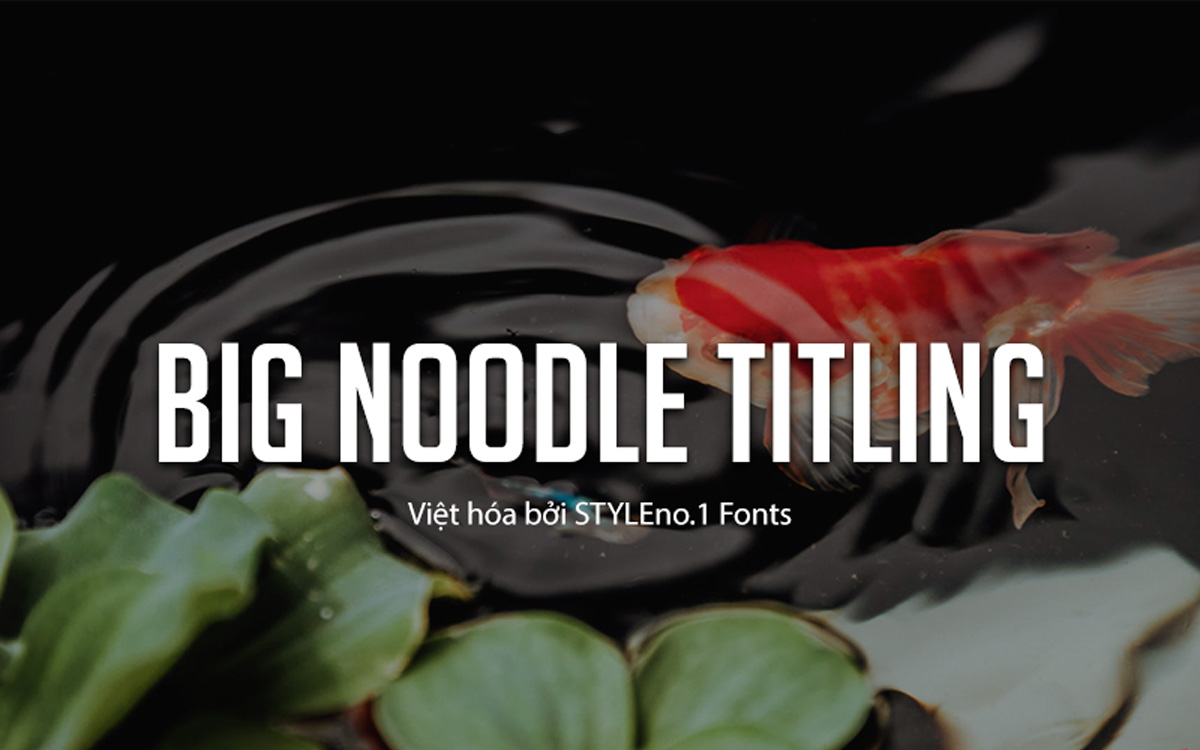
Trong thế giới thiết kế đồ họa đương đại, việc lựa chọn font chữ phù hợp đóng vai trò quyết định đến thần thái, giá trị thẩm mỹ và thông điệp của toàn bộ tác phẩm. Font chữ SVN Big Noodle Titling là một trong những bộ font Việt hóa hàng đầu, nổi bật với phong cách thanh lịch, hiện đại và vô cùng sang trọng. Với kiểu dáng cô đọng (condensed) mạnh mẽ nhưng không kém phần tinh tế, bộ phông chữ này đã trở thành sự lựa chọn ưu tiên của các designer chuyên nghiệp khi sáng tạo thiệp cưới cao cấp, ấn phẩm thời trang và các trang tạp chí nghệ thuật.
Font Chữ Thanh Lịch, Hiện Đại, Sang Trọng SVN Big Noodle Titling – Giải Pháp Thiết Kế Thiệp Cưới, Thời Trang Và Tạp Chí Đỉnh Cao
Phông chữ SVN Big Noodle Titling được phát triển dựa trên nguyên bản Big Noodle Titling nổi tiếng thế giới của tác giả Sentinel Type, sau đó được tích hợp hệ thống ký tự tiếng Việt đầy đủ và tối ưu hóa bởi cộng đồng SVN. Bộ font này mang trong mình vẻ đẹp tối giản của nghệ thuật typography hiện đại, kết hợp hài hòa giữa cấu trúc hình học chuẩn xác và chiều cao lý tưởng. Nhờ sự cân bằng hoàn hảo giữa tính thẩm mỹ thời thượng và khả năng thu hút thị giác mạnh mẽ, SVN Big Noodle Titling không chỉ đơn thuần là một công cụ hiển thị văn bản mà còn là điểm nhấn nghệ thuật nâng tầm giá trị cho mọi sản phẩm thiết kế.
Đối với các dự án đòi hỏi tính thẩm mỹ khắt khe như nhận diện thương hiệu thời trang cao cấp, bìa tạp chí hàng hiệu hay thiệp cưới mang phong cách Minimalist Modern, SVN Big Noodle Titling mang lại một hơi thở hoàn toàn mới. Bộ font giúp truyền tải thông điệp một cách rõ ràng, sắc nét, thể hiện sự chuyên nghiệp và gu thẩm mỹ tinh tế của người sáng tạo.
1. Thiết Kế Cô Đọng (Condensed) Độc Đáo, Tạo Ấn Tượng Thị Giác Mạnh Mẽ
Điểm đặc trưng nhất của SVN Big Noodle Titling chính là cấu trúc chữ dạng cô đọng (condensed) với các nét đứng vươn cao, thanh thoát nhưng cực kỳ chắc chắn. Kiểu dáng này mang lại nhiều lợi thế vượt trội cho các nhà thiết kế đồ họa:
- Tiết kiệm diện tích hiển thị: Nhờ chiều rộng chữ được thu gọn tối ưu, bạn có thể dễ dàng sắp xếp các tiêu đề dài trên một dòng duy nhất mà không lo vỡ khung hình hay thu nhỏ kích thước chữ quá mức.
- Tạo điểm nhấn thị giác ngay lập tức: Các đường nét thẳng, sắc sảo và tỷ lệ khung chữ cao giúp tiêu đề trở nên nổi bật tuyệt đối trên nền thiết kế, thu hút ánh nhìn của người xem ngay từ giây đầu tiên.
- Phong cách hiện đại và tối giản: Loại bỏ các chi tiết chân chữ (sans-serif) rườm rà, font chữ hướng tới sự tinh gọn, phù hợp với xu hướng thiết kế phẳng và phong cách thiết kế Châu Âu đương đại.
2. Bản Việt Hóa Hoàn Chỉnh, Tinh Tế Đến Từng Dấu Thanh Tiếng Việt
Một trong những thách thức lớn nhất khi sử dụng các phông chữ nước ngoài vào thiết kế tiếng Việt là sự mất cân đối do các dấu thanh (sắc, huyền, hỏi, ngã, nặng) làm phá vỡ khoảng cách dòng. SVN Big Noodle Titling đã giải quyết triệt để vấn đề này nhờ quy trình Việt hóa chỉn chu:
- Hệ thống dấu tiếng Việt được vẽ lại tỉ mỉ: Dấu câu và dấu thanh được thiết kế riêng biệt để tương thích hoàn hảo với độ cao và độ dày nét của từng chữ cái gốc, đảm bảo tính nhất quán trực quan.
- Khoảng cách chữ (Kerning) chuẩn xác: Tối ưu hóa khoảng cách giữa các ký tự có dấu, giúp văn bản tiếng Việt khi trình bày không bị dính nét hoặc đứt đoạn vô lý.
- Giữ nguyên tinh thần bản gốc: Dù được bổ sung trọn bộ ký tự tiếng Việt, font chữ vẫn duy trì trọn vẹn sự thanh lịch, sang trọng và phóng khoáng ban đầu.
3. Giải Pháp Tối Ưu Cho Thiết Kế Thiệp Cưới Hiện Đại Và Sang Trọng
Xu hướng thiết kế thiệp cưới hiện nay đang dịch chuyển mạnh mẽ từ phong cách cổ điển, rườm rà sang phong cách hiện đại, tinh gọn và sang trọng. SVN Big Noodle Titling chính là “mảnh ghép hoàn hảo” cho sự thay đổi này:
Khi được ứng dụng trong thiết kế thiệp cưới, font chữ này thường được dùng cho các phần thông tin quan trọng như tên chú rể – cô dâu, ngày tháng tổ chức hoặc địa điểm lễ cưới. Độ cao vút của chữ tạo nên cảm giác trang trọng, tinh tế. Đặc biệt, khi kết hợp SVN Big Noodle Titling (dùng làm tiêu đề chính) với các phông chữ viết tay (script font) mềm mại hoặc phông chữ có chân (serif font) cổ điển, tác phẩm thiệp cưới sẽ đạt được sự tương phản nghệ thuật tuyệt đẹp – vừa mạnh mẽ, cá tính lại vừa dịu dàng, lãng mạn.
4. Biểu Tượng Cho Ngành Thời Trang, Bìa Tạp Chí Và Ấn Phẩm Quảng Cáo Cao Cấp
Không ngẫu nhiên mà SVN Big Noodle Titling luôn nằm trong top các font chữ được các Art Director trong ngành thời trang ưa chuộng nhất. Tính chất thời thượng và sang trọng của bộ font này đáp ứng trọn vẹn các yêu cầu khắt khe của ngành công nghiệp sáng tạo:
- Bìa tạp chí và Editorial Layout: Font chữ hoàn hảo cho các tiêu đề bài viết (Headline), tên tạp chí hoặc các câu trích dẫn nổi bật (Pull-quote) trên các trang tạp chí thời trang, kiến trúc và lối sống.
- Branding & Catalogue thời trang: Tạo nên sự đẳng cấp khi xuất hiện trên Lookbook, banner quảng cáo bộ sưu tập mới, nhãn mác quần áo hoặc bao bì sản phẩm hàng hiệu.
- Poster sự kiện và triển lãm: Thể hiện thần thái nghệ thuật cao cấp, thích hợp cho các buổi diễn thời trang (Fashion Show), triển lãm mỹ thuật hay sự kiện âm nhạc sang trọng.